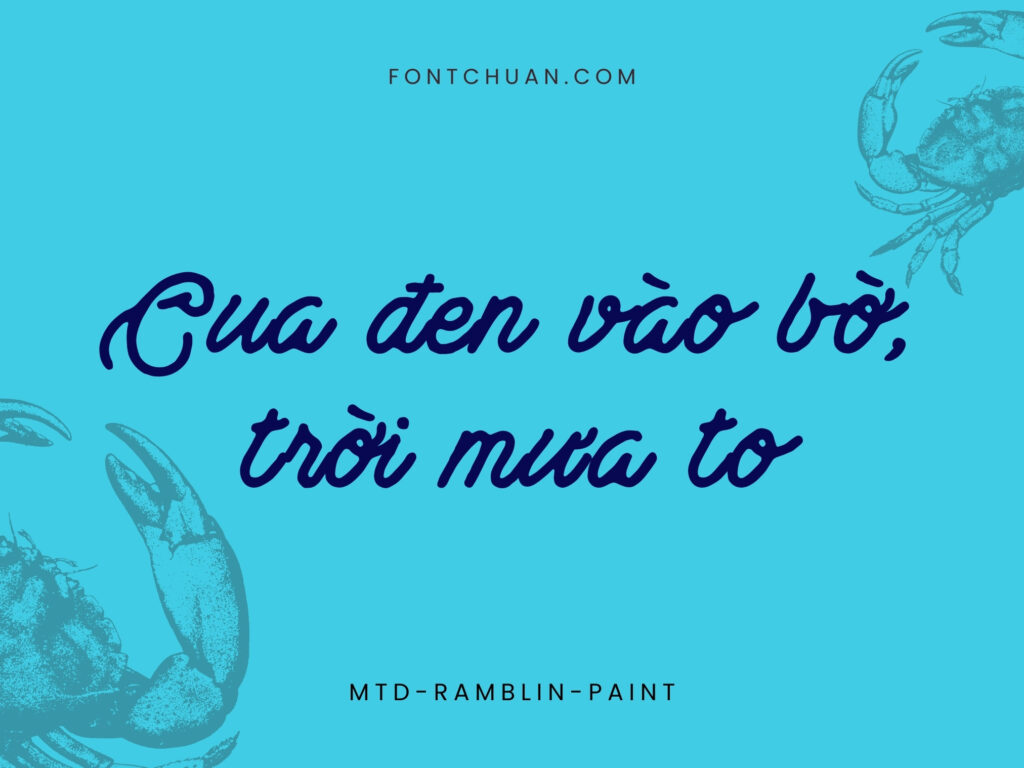
Font MTD Ramblin Paint Việt Hóa
Tác giả Font: Burntilldead
Font MTD Ramblin Paint là một phông chữ script lấy cảm hứng từ nét cọ vẽ tay tự nhiên, được thiết kế bởi Letterhend Studio và phát hành trên Envato Elements. Font đã được Việt hóa bởi Mộc Hạ, hỗ trợ tiếng Việt và hơn 90 ngôn ngữ khác, giúp mở rộng khả năng ứng dụng trong các thiết kế đa ngôn ngữ. Đây là một trong những phông chữ được cộng đồng thiết kế đánh giá cao và ứng dụng trong nhiều dự án sáng tạo, đáp ứng nhu cầu đa dạng của người dùng.
MTD Ramblin Paint nổi bật với các đường nét tự nhiên và phong cách thủ công, mang đến cảm giác mộc mạc và chân thực. Font rất phù hợp cho các thiết kế logo, tiêu đề, bao bì sản phẩm, thiệp mời và các ấn phẩm đòi hỏi sự sáng tạo và cá nhân hóa. Các ngành nghề phù hợp bao gồm quảng cáo, giáo dục, công nghệ, thiệp cưới và ảnh cưới. Font này cũng lý tưởng cho các sự kiện như Tết, Giáng sinh, Valentine và các lễ hội khác.